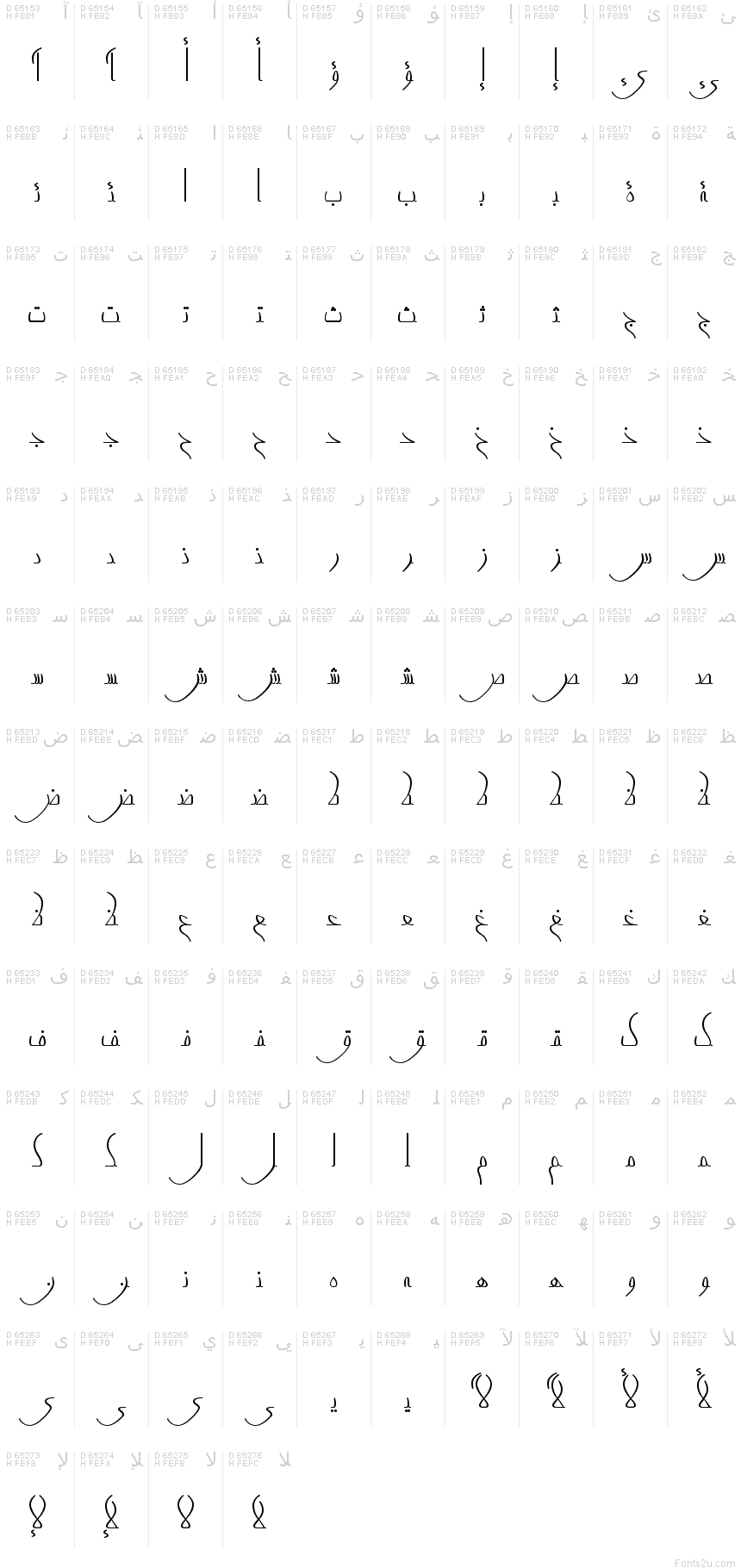
B Narenj, créée par Borna Rayaneh, est une police arabe gratuite aux caractères élancés et fluides, marqués par de longs traits verticaux et des courbes douces et sobres. Son design est élégant sans jamais être chargé, misant sur une belle hauteur et un rythme épuré pour offrir au texte arabe une présence contemporaine et raffinée.
Ses proportions équilibrées la rendent idéale pour le branding culturel, la mise en page éditoriale, les couvertures de livres, le packaging et la signalétique d'exposition, où la calligraphie arabe occupe une place centrale. Cette police gratuite et polyvalente est également parfaite pour les titres, les génériques et tout texte d'affichage court qui gagne à être mis en valeur par sa grâce verticale.
Table des caractères de la police B Narenj
Table des caractères de B Narenj : Formes-B de présentation arabe, page 1
Glyphes de la police B Narenj — Formes-B de présentation arabe, page 1